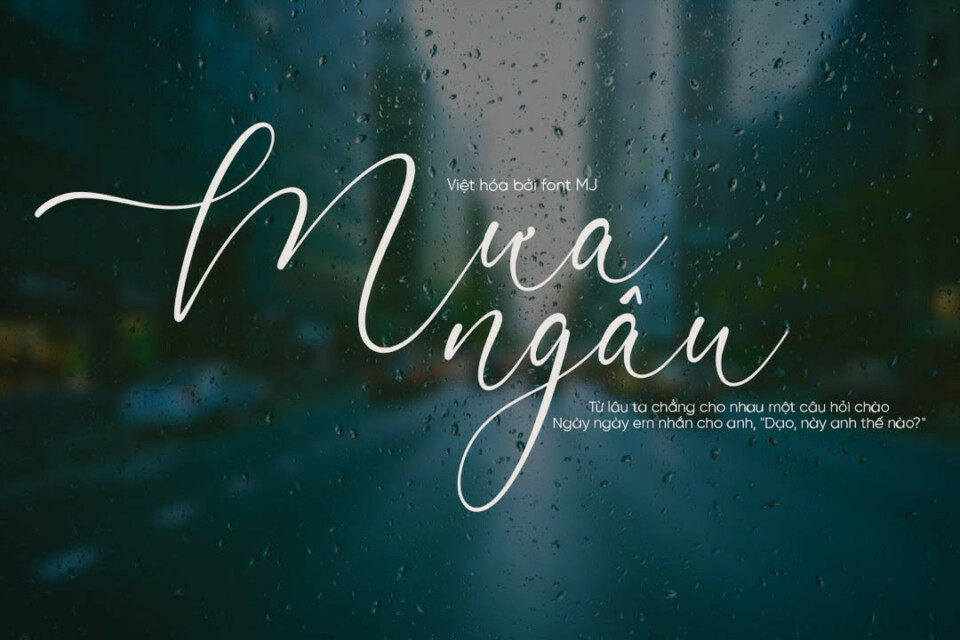
Trong thế giới thiết kế đồ họa đầy cạnh tranh hiện nay, việc lựa chọn một Font Chữ phù hợp có thể tạo nên sự khác biệt đáng kể cho tác phẩm của bạn. Đối với những ai đang tìm kiếm một phông chữ không chỉ đẹp mắt mà còn mang đậm dấu ấn cá nhân và khả năng tương thích cao với tiếng Việt, **Font việt hoá MJ VIP Daytonica** chính là một lựa chọn không thể bỏ qua. Phông chữ này không chỉ nổi bật với vẻ ngoài độc đáo mà còn được tối ưu hóa hoàn hảo cho người dùng Việt Nam, hứa hẹn mang lại trải nghiệm thiết kế mượt mà và hiệu quả. Bài viết này sẽ đi sâu vào khám phá những đặc điểm nổi bật, ứng dụng và lý do tại sao MJ VIP Daytonica lại là sự bổ sung giá trị cho bộ sưu tập font của bạn.
Khám phá vẻ đẹp và tính năng của Font việt hoá MJ VIP Daytonica
MJ VIP Daytonica là một phông chữ hiện đại, mang trong mình sự kết hợp tinh tế giữa nét cổ điển và hơi thở đương đại. Thiết kế của nó toát lên vẻ sang trọng, thanh lịch nhưng không kém phần mạnh mẽ và cá tính. Điểm đặc biệt làm nên sự khác biệt của phông chữ này chính là quá trình việt hóa công phu. Nhờ sự tỉ mỉ trong việc thêm các dấu tiếng Việt, từ dấu sắc, huyền, hỏi, ngã, nặng cho đến các chữ cái đặc trưng như Đ, Ư, Ơ, MJ VIP Daytonica đã trở thành một công cụ mạnh mẽ, giúp các nhà thiết kế Việt Nam tự do sáng tạo mà không lo lắng về vấn đề hiển thị sai lệch hay thiếu ký tự. Mỗi ký tự đều được điều chỉnh để đảm bảo tính thẩm mỹ và khả năng đọc tốt nhất, dù là trên màn hình kỹ thuật số hay trong các ấn phẩm in ấn.
Ưu điểm nổi bật của Font MJ VIP Daytonica
- Tính Thẩm Mỹ Cao: Với các đường nét mềm mại nhưng dứt khoát, MJ VIP Daytonica mang lại vẻ ngoài chuyên nghiệp và thu hút. Nó phù hợp với nhiều phong cách thiết kế khác nhau, từ tối giản đến phức tạp.
- Việt Hóa Hoàn Chỉnh: Đây là một trong những ưu điểm lớn nhất. Việc việt hóa kỹ lưỡng giúp phông chữ này hiển thị tiếng Việt một cách hoàn hảo, không gặp lỗi chính tả hay lỗi hiển thị ký tự. Điều này đặc biệt quan trọng cho các tài liệu giáo dục, sách vở, hay các ấn phẩm hướng đến học sinh, sinh viên.
- Dễ Đọc và Dễ Sử Dụng: Mặc dù có phong cách độc đáo, MJ VIP Daytonica vẫn giữ được tính dễ đọc cao, giúp người xem tiếp thu thông tin một cách dễ dàng. Các nhà thiết kế cũng có thể dễ dàng tích hợp nó vào các phần mềm thiết kế phổ biến.
- Tính Đa Dụng: Phông chữ này có thể được sử dụng trong nhiều ngữ cảnh khác nhau, từ thiết kế logo, bộ nhận diện thương hiệu, poster quảng cáo, bao bì sản phẩm, cho đến các ấn phẩm cá nhân hay bài thuyết trình học đường.
Ứng dụng đa dạng của Font việt hoá MJ VIP Daytonica trong thiết kế
Với vẻ đẹp độc đáo và khả năng việt hóa ưu việt, **Font việt hoá MJ VIP Daytonica** có thể phát huy tối đa tiềm năng trong nhiều lĩnh vực:
- Thiết Kế Thương Hiệu: Mang lại sự sang trọng và khác biệt cho logo, danh thiếp, và các tài liệu marketing của doanh nghiệp.
- Quảng Cáo và Truyền Thông: Phù hợp cho các tiêu đề, slogan trên poster, banner, và các ấn phẩm truyền thông, thu hút sự chú ý ngay lập tức.
- Ấn Phẩm Giáo Dục và Học Đường: Từ bìa sách, giáo trình đến các tài liệu ôn thi tốt nghiệp, phông chữ này giúp tạo ra sự chuyên nghiệp và dễ nhìn cho học sinh và giáo viên.
- Thiết Kế Website và Ứng Dụng: Góp phần tạo nên giao diện người dùng thân thiện, hiện đại và dễ đọc.
- Nghệ Thuật và Trang Trí: Dùng trong các dự án cá nhân, thiệp mời, tranh ảnh trang trí để thể hiện phong cách riêng.
Sự linh hoạt này khiến MJ VIP Daytonica trở thành một tài sản quý giá cho bất kỳ nhà thiết kế nào muốn mang lại sự tinh tế và chuyên nghiệp cho tác phẩm của mình. Đặc biệt, đối với các trường học, trung tâm luyện thi, hay các dự án dành cho học sinh, sinh viên, việc sử dụng một phông chữ đẹp và dễ đọc như Daytonica có thể cải thiện đáng kể trải nghiệm học tập và tiếp nhận thông tin.
Tại sao nên chọn Font việt hoá MJ VIP Daytonica cho dự án của bạn?
Chọn đúng phông chữ không chỉ là vấn đề thẩm mỹ mà còn là chiến lược. **Font việt hoá MJ VIP Daytonica** cung cấp một giải pháp toàn diện cho những ai cần một phông chữ chất lượng cao, có khả năng hiển thị tiếng Việt hoàn hảo và mang đậm phong cách. Trong bối cảnh nội dung tiếng Việt ngày càng phong phú, việc có một công cụ hỗ trợ mạnh mẽ như Daytonica sẽ giúp bạn vượt trội so với đối thủ. Nó không chỉ giúp bạn truyền tải thông điệp một cách rõ ràng mà còn tạo ra ấn tượng mạnh mẽ và khó quên với người xem. Sự đầu tư vào một phông chữ chất lượng như thế này sẽ mang lại giá trị lâu dài cho các dự án của bạn, từ quy mô nhỏ đến lớn, từ cá nhân đến doanh nghiệp, và đặc biệt là trong lĩnh vực giáo dục, nơi sự rõ ràng và chuyên nghiệp là yếu tố then chốt.
Hơn nữa, việc sử dụng các phông chữ được việt hóa chuyên nghiệp thể hiện sự tôn trọng đối với ngôn ngữ mẹ đẻ và giúp nâng cao chất lượng tổng thể của các ấn phẩm tiếng Việt. Đối với các trường học hoặc tổ chức giáo dục, việc sử dụng một phông chữ đẹp và dễ đọc trong các tài liệu học tập có thể ảnh hưởng tích cực đến trải nghiệm của học sinh, giúp các em tập trung hơn vào nội dung mà không bị phân tâm bởi các vấn đề hiển thị font.
Lưu ý khi sử dụng Font MJ VIP Daytonica
Để tận dụng tối đa vẻ đẹp của MJ VIP Daytonica, bạn nên cân nhắc một số yếu tố. Phông chữ này thường rất nổi bật khi được dùng làm tiêu đề hoặc nhấn mạnh các đoạn văn quan trọng. Khi kết hợp với các phông chữ khác, hãy chọn những phông chữ có nét đơn giản, thanh lịch để tạo sự cân bằng và không làm mất đi vẻ đẹp của Daytonica. Tránh sử dụng nó cho các đoạn văn bản quá dài với kích thước nhỏ, vì điều này có thể làm giảm khả năng đọc. Luôn kiểm tra kỹ lưỡng hiển thị trên nhiều thiết bị và nền tảng khác nhau để đảm bảo tính nhất quán.
Tóm lại, **Font việt hoá MJ VIP Daytonica** là một lựa chọn tuyệt vời cho các nhà thiết kế đang tìm kiếm sự kết hợp giữa phong cách, chất lượng và khả năng hỗ trợ tiếng Việt ưu việt. Nó không chỉ là một phông chữ mà còn là một công cụ để bạn thể hiện sự sáng tạo và chuyên nghiệp trong mọi dự án.
Trong thế giới thiết kế đầy biến động, việc sở hữu một Font Chữ chất lượng cao, đặc biệt là một phông chữ đã được việt hóa tỉ mỉ như **Font việt hoá MJ VIP Daytonica**, sẽ là lợi thế cạnh tranh đáng kể. Hãy để MJ VIP Daytonica đồng hành cùng bạn, biến mọi ý tưởng thành hiện thực với phong cách độc đáo và ấn tượng.